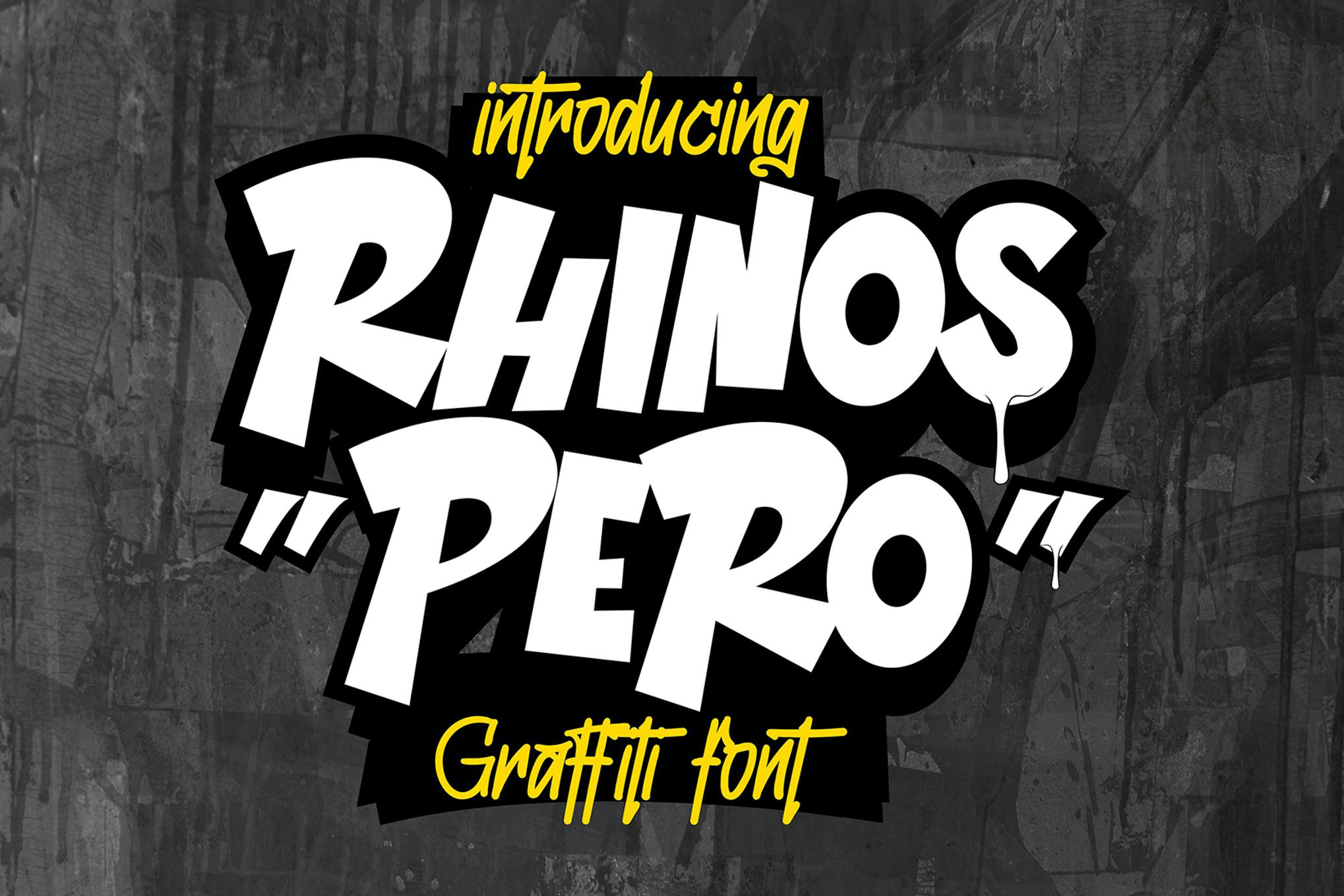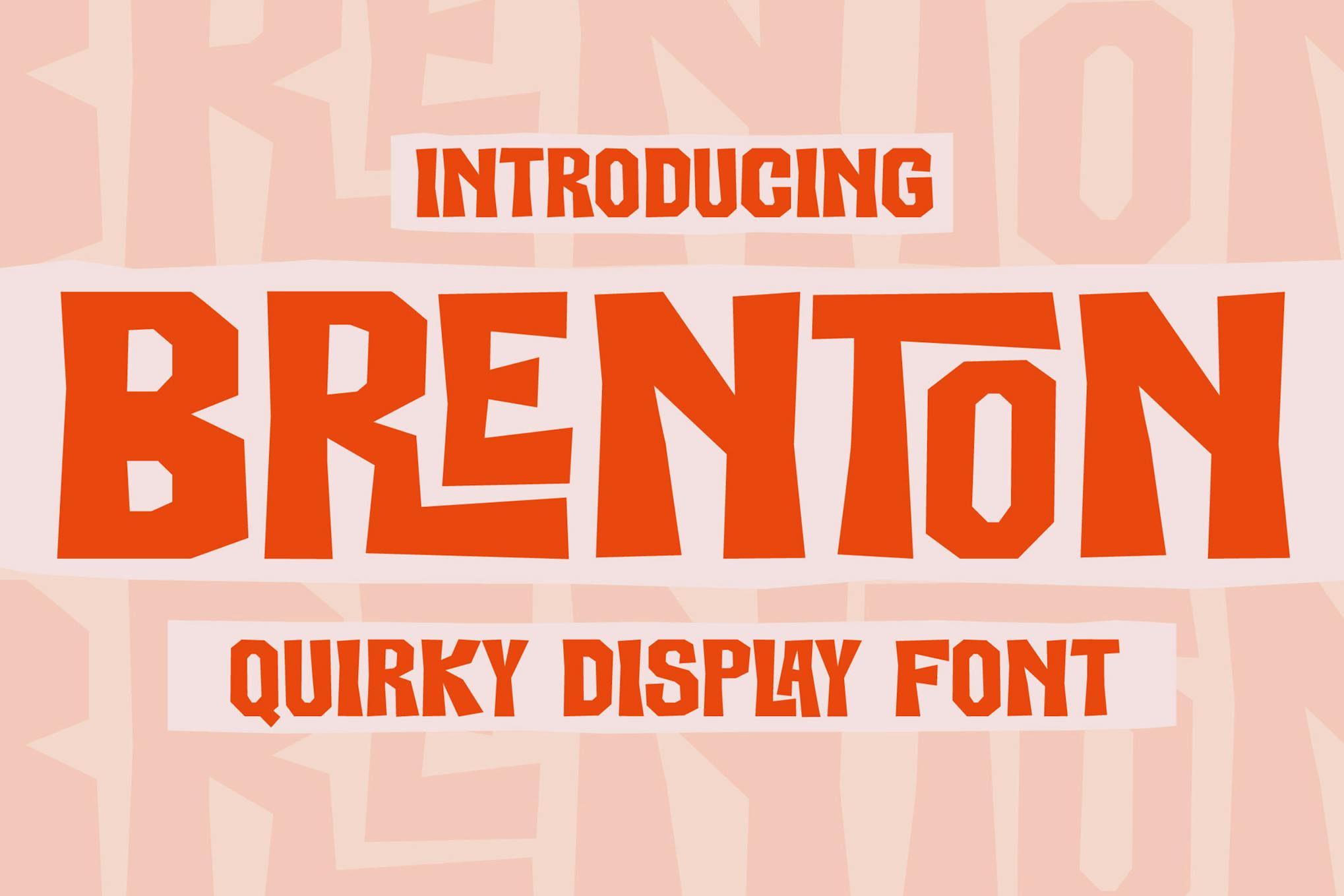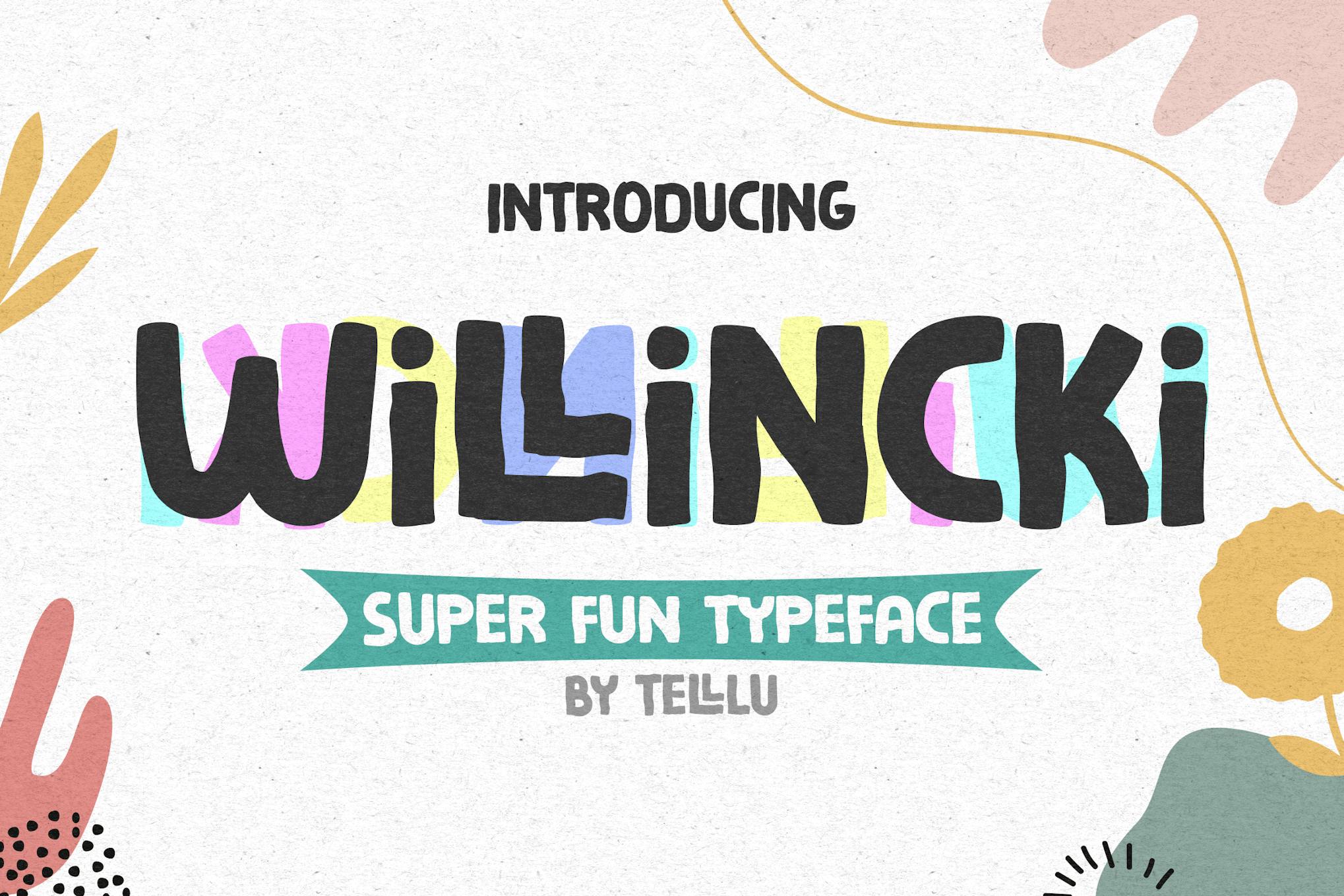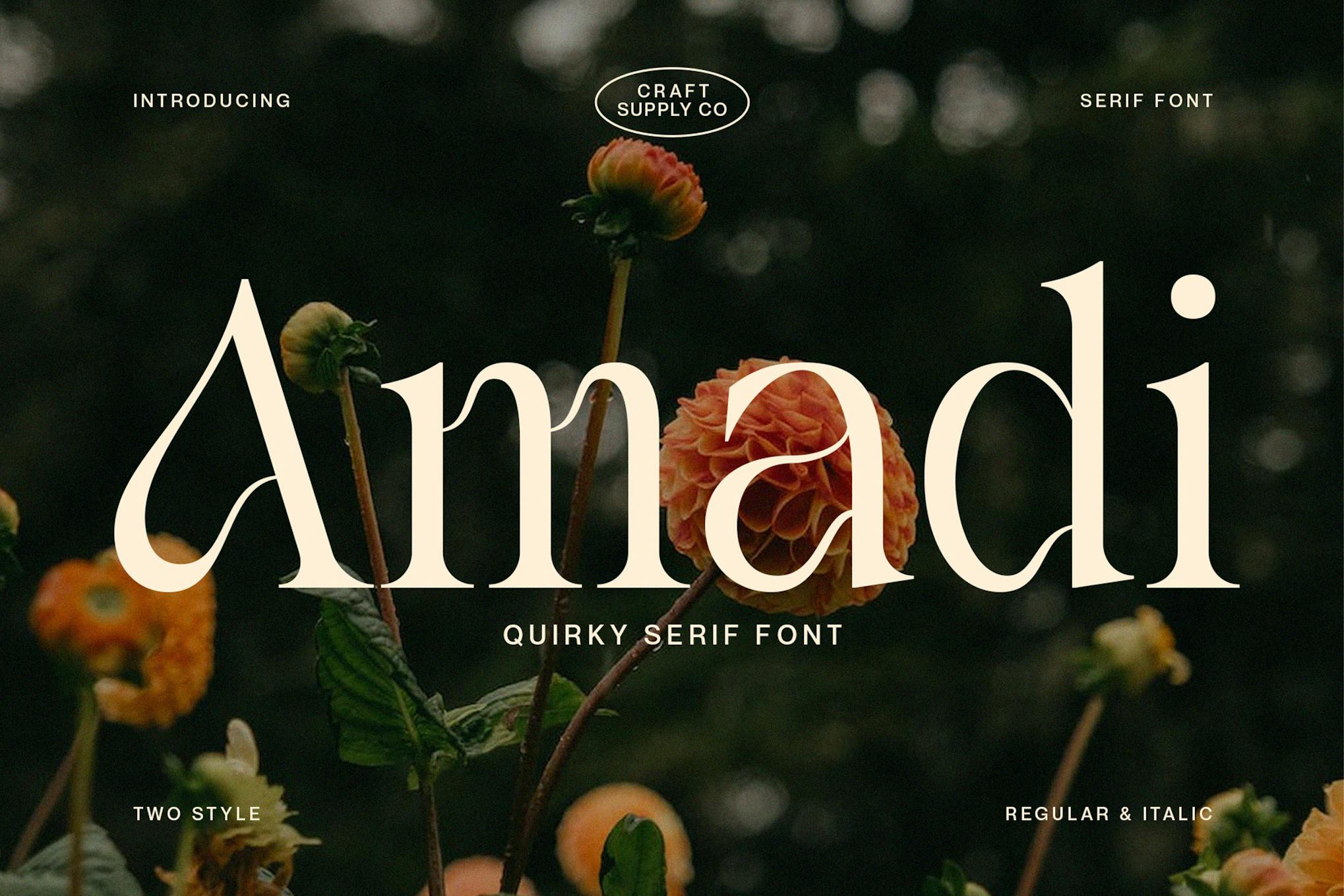
25+ Skurrile Schriftarten, die neue Maßstäbe setzen
Schriftarten können eine Geschichte genauso lebhaft erzählen wie die Wörter, die sie bilden, und eigenwillige Schriftarten zeichnen sich durch ihre Fähigkeit aus, Humor, Charakter und einen unbestreitbaren Charme in Ihre Arbeit einzubringen.
In diesem Beitrag präsentieren wir Ihnen eine Sammlung von sowohl kostenlosen als auch Premium-eigenwilligen Schriftarten. Von verspielter Kalligrafie bis hin zu unkonventionellen Blockbuchstaben haben wir diese Schriftartensammlung entworfen, um Ihnen zu helfen, Ihren kreativen Projekten eine Prise Originalität hinzuzufügen.
Tauchen Sie ein und entdecken Sie diese fantastischen Schriftarten, die versprechen, Ihren Designprojekten eine einzigartige Persönlichkeit zu verleihen. Brechen Sie aus dem Gewohnten aus und lassen Sie Ihre Designs mit diesen eigenwilligen und verspielten Schriftarten eine Geschichte erzählen, die wirklich aus dem Rahmen fällt.
Rhinos Pero - Eigenwillige Graffiti-Schriftart
Rhinos Pero ist eine einzigartige Graffiti-Schriftart mit einem lustigen, eklektischen Stil. Ausgezeichnet durch ihre unregelmäßigen Formen und verspielten Zeichen, bietet sie einen unkonventionellen Reiz. Geeignet für Projekte, die einen verspielten Touch benötigen, enthält sie Rhinos Pero in den Formaten TTF, OTF und WOFF und unterstützt mehrsprachige und Interpunktionsfunktionen.
Brenton - Eigenwillige Display-Schriftart
The Brenton ist eine markante Schriftart, die Ihren Projekten eine einzigartige, eigenwillige Note verleiht. Ideal für Poster, Social-Media-Beiträge, Branding oder persönliche Vorhaben, haucht diese Schriftart Ihren digitalen und gedruckten Kreationen Leben ein. Sie kommt in den Formaten OTF, WOFF und TTF, was sie vielseitig für verschiedene Anforderungen macht.
Willincki - Eine eigenwillige und verspielte Schriftart
Adoptieren Sie einen Sinn für Spaß und Verspieltheit mit Willincki, einer verspielten und eigenwilligen Schriftart. Mit ihrem lebendigen Charakter vermittelt diese lockere Schriftart eine starke Botschaft und eignet sich daher für Schul- oder Wissenschaftsprojekte, Buchumschläge oder Präsentationstitel. Ihre Vielseitigkeit erstreckt sich auch auf die kulinarische Welt; geeignet für Foodtrucks, Restaurants, Menüs und Branding-Materialien.
Little Things - Eigenwillige Display-Schriftart
Little Things ist eine eigenwillige Display-Schriftart, die sowohl markant als auch kühn ist. Perfekt geeignet für die Gestaltung von Webdesigns, Visitenkarten oder anderen Artefakten, die einen modernen, futuristischen Reiz erfordern. Mit Little Things erhalten Sie die Formate OTF, TTF, WOFF und WOFF2.
White Beach - Eigenwillige Handschrift-Schriftart
White Beach ist eine spielerische und kreative Schriftart, die perfekt für DIY-Bastler und diejenigen ist, die Cricut und Canva verwenden. Erhältlich in den Formaten OTF und TTF, unterstützt sie auch Webfonts (WOFF) und mehrere Sprachen. Ihre Einzigartigkeit wird Ihren Projekten sicherlich eine spaßige Note verleihen.
Weird Genius - Eigenwillige Display-Schriftart
Weird Genius ist eine lebendige und vielseitige Schriftart, die verschiedene kreative Projekte verbessern kann. Ihre Einfachheit und ihr Charme passen nahtlos in eine Vielzahl von Anwendungen, von Websites und Blogs bis hin zu Shirt-Designs und Kinderdesigns. In mehreren Formaten wie OTF, TTF und WOFF erhältlich, ist sie nicht nur leicht zu lesen, sondern auch äußerst anpassungsfähig und verleiht Zitaten, Branding, Logos und Einladungen eine Einzigartigkeit.
Delrosa - Urlaubseigentümliche Schriftart
Delrosa ist eine exzentrische, aber äußerst vielseitige Schriftart, die ideal ist, um Ihre digitalen und gedruckten Arbeiten aufzupeppen. Perfekt für Social-Media-Beiträge, Branding, Poster, persönliche Projekte und mehr verleiht sie eine einzigartige Note, mit der Ihre Kreationen hervorstechen. Delrosa ist in den Formaten OTF, WOFF und TTF erhältlich und bereit, Kreativität in Ihre festlichen Urlaubsprojekte zu bringen.
Juggler - Trendige eigenwillige Schriftart
Juggler ist eine trendige und eigenwillige Schriftart mit zerklüfteten, federnden Linien, die Energie und Attitüde ausstrahlen. Ihr direkter Stil macht sie perfekt für kraftvolle Zitate und motivierende Phrasen. Kompatibel mit mehreren Sprachen ist Juggler in den Formaten OTF, TTF und WOFF erhältlich und bietet flexible Optionen für Ihre Designbedürfnisse.
Asterluck - Eigenwillige Display-Schriftart
Der Asterluck ist eine eigenwillige Schriftart, die mit ihrem spielerischen Charakter perfekt auf lockere Designthemen zugeschnitten ist. Am besten geeignet zur Erstellung von Logos kann sie auch auf verschiedene formelle Formulare wie Einladungen, Etiketten, Bücher und mehr angewendet werden. Er verfügt über Groß- und Kleinbuchstaben, Zahlen, Interpunktion, mehrsprachige Unterstützung und PUA-Codierung.